These monospaced fonts, designed for programmers, make code easier to read and understand. But why use monospace fonts for programming? Well, monospace fonts allocate equal space to each character, meaning the letter “i” is given the same horizontal space as the letter “k.” This might seem unnatural for other types of text and printing, but it’s ideal for programming.
This is because numbers and punctuation are much easier to read when they are evenly spaced. A single font also makes it easier to achieve indentation and vertical alignment, both of which are important for code clarity.
Below we’ve selected the best monospace fonts for programming. Some are paid, while others are free, but special care has been taken to ensure that punctuation is larger than usual, glyphs are easily distinguishable, and the typeface can be comfortably viewed during long programming sessions. Some of these options are customizable (see our font design guide to help create your own).
01. Mona Lisa
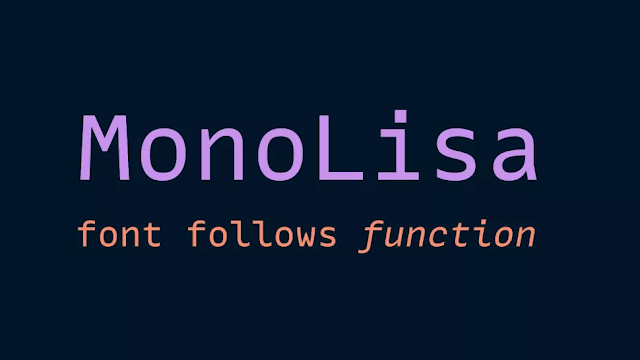
MonoLisa is specifically designed to improve developer productivity and reduce fatigue, and it’s a remarkably clear font. It ensures all glyphs are the same width for easy readability, yet it’s not boring. It boasts a feature set that includes increased character width, clear highlighting, and excellent readability.
02. أبيركو مونو
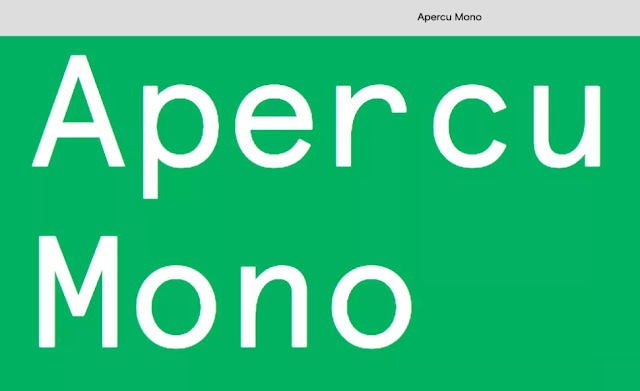
Apercu Mono هو جزء من عائلة خطوط Apercu الأكبر بكثير. تم تصميمه بواسطة The Entente ، وهو جزء من مسبك نوع Colophon الحائز على جائزة ومقره في لندن (المملكة المتحدة) ولوس أنجلوس (الولايات المتحدة). يتمتع المسبك بسمعة طيبة في إنشاء محارف عالية الجودة ونشرها وتوزيعها للوسائط التناظرية والرقمية ، وهذا مثال على ذلك.
كان المفهوم الأصلي وراء Apercu هو إنشاء مزيج من الخطوط الواقعية الكلاسيكية مثل Johnston و Gill Sans و Neuzeit و Franklin Gothic. أنشأ الفريق عائلة واسعة وقابلة للاستخدام بما في ذلك إصدار Mono المثالي لعرض الكود.
يتضمن الإصدار Mono الآن أربعة أشكال مختلفة – Mono Light و Mono Regular و Mono Medium و Mono Bold. تتضمن عائلة الخطوط القياسية الأحرف الكبيرة والصغيرة ، و 72 لهجة وزوج من الأحرف المزدوجة عبر جميع الأوزان. يضيف الإصدار المحترف صورًا رمزية للأرقام من الطراز القديم ، و 100 رمزًا والمزيد من الأحرف المركبة – أكثر من كافية لأي مبرمج.
03. كود فيرا
Fira Code هو امتداد لـ Fira Mono ، وهو خط أحادي المسافة مصمم من طرف موزيلا ليلائم طابع نظام التشغيل Firefox OS. يشتمل متغير رمز Fira على حروف مركبة للبرمجة – عروض خاصة لمجموعات أحرف معينة مصممة لتسهيل قراءة وفهم الكود. لذلك ، على سبيل المثال ، يتم تقديم تركيبات == و! = على أنها صور رمزية مناسبة للمساواة ، والتي من المفترض أن يكون من السهل على الدماغ معالجتها من حرفين منفصلين لهما معاني فردية خاصة بهما.
ما تشعر به حيال هذا يعتمد بالطبع على الذوق الشخصي. إذا كنت قد قرأت بالفعل رمزًا عاديًا لسنوات ، فهناك احتمال كبير أنك قد لا ترغب في إجراء التغيير. ولكن إذا كان هذا الأمر جذابًا ، فإن Fira Code هو خط برمجة شائع ومدعوم على نطاق واسع يجعل الكود سهل القراءة. إنه أيضًا مجاني ومفتوح المصدر. تحتوي صفحة GitHub على نماذج ترميز من مجموعة من اللغات حتى تتمكن من رؤية كيف تبدو الأشياء.
04. Input Mono
Input عبارة عن نظام للخطوط مصمم خصيصًا للبرمجة بواسطة David Jonathan Ross. يأتي في كل من المتغيرات النسبية وحيدة المسافة ، ولكن نظرًا لأنه تم تصميمه مع وضع الترميز في الاعتبار ، فإن التباعد النسبي مصمم خصيصًا ، لذلك يمكنك اعتباره على الإصدار أحادي المسافة.
هناك مجموعة من العروض والأوزان والأنماط ، كل منها يحتوي على متغيرات serif و sans و monospace ، مما ينتج عنه 168 نمطًا مختلفًا في المجموع. هذا يعني أنه يمكنك حقًا الحصول على ما تريد من مجموعة الخطوط هذه. تم وصفه بأنه يحتوي على مسافات كبيرة ، وعلامات ترقيم كبيرة ، وحروف يمكن تمييزها بسهولة ، وقد تم إيلاء الكثير من الاهتمام لحجم ومواضع الرموز المستخدمة بشكل متكرر في الترميز. يمكنك أيضًا تخصيص أشكال بعض الأحرف الرئيسية بما في ذلك الأحرف “i” و “l” و “a” و “g”.
05. دانك مونو
تم وصف Dank Mono من Phil Plückthun على أنه خط “مصمم للجماليات مع وضع الشفرة وشبكة Retina في الاعتبار”. مثل Fira Code ، فإنه يحتوي على حروف مركبة ، وهناك أيضًا متغير مائل مخطوطة مفيد في التمييز بين أنواع مختلفة من النص داخل الكود الخاص بك. بشكل عام ، تم إنشاء هذا الخط للمبرمجين الذين لديهم اهتمام بالتصميم ، والحروف الصغيرة غير العادية “f” معروفة بأنها محبوبة بشكل خاص بين عشاق Dank.
يدعم Dank مجموعات الأحرف اللاتينية الغربية والشرقية والوسطى والجنوبية الأوروبية ، ويمكنك استخدامها داخل CodePen. للحصول على Dank ، ستحتاج إلى الدفع – الترخيص الشخصي هو 24 جنيهًا إسترلينيًا والرخصة التجارية 60 جنيهًا إسترلينيًا. ولكن إذا كنت متذوقًا من النوع وكنت مغرمًا بهذا الحرف “ f ” ، فقد يكون من المفيد أن تعامل نفسك ببعض القذارة.
06. جينترونيك
يصف المنشئ مارك فرومبيرج Gintronic بأنه “مرح” و “لطيف” – وهو ترياق لما يراه أسلوبًا تقنيًا وميكانيكيًا للغاية للعديد من خطوط البرمجة. الخط مريح وسهل النظر إليه ، مع إضافة بعض الأحرف الخاصة إلى شخصية خاصة – تحقق من الأقواس المتعرجة وعلامة الاستفهام والحرف الصغير “k” والأرقام. تم إيلاء اهتمام إضافي للصور الرمزية التي يصعب التمييز بينها ، مثل “B” و “8” و “i” و “l” وما إلى ذلك ، وذلك لتسهيل تمييزها في لمح البصر.